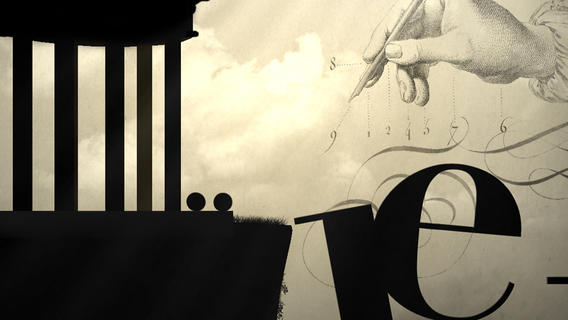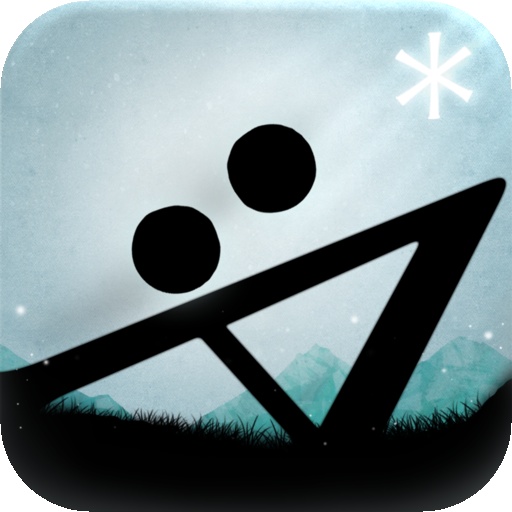
Pur essendo un gioco platform con elementi puzzle da risolvere Type:Rider di BulkyPix per iPhone e iPad brilla per la parte creativa e l’originalità del game design. Ogni elemento del gioco, i protagonisti e gli scenari sono infatti realizzati attingendo alla storia e agli elementi della tipografia: l’utente controlla due palline che devono rotolare e scalare percorsi costruiti con lettere e simboli grafici. I protagonisti, che sono la rappresentazione grafica dei due punti, iniziano il viaggio nel primo livello ispirato alle prime incisioni su pietra realizzate dall’uomo all’interno delle caverne, per proseguire lungo i 10 mondi in un affascinante viaggio che presenta gli uomini, le opere e soprattutto i font e gli stili grafici tipici di ogni epoca.
In puro stile platform dovremo così superare percorsi e baratri creati con lettere e caratteri proseguendo tra i geroglifici egiziani, la scrittura cinese, fino a epoche storiche più recenti come la frontiera americana dell’800 fino ad arrivare ai caratteri e alla grafica su computer. Nel corso del gioco l’utente dovrà raccogliere diverse lettere e potrà ammirare diverse tra le font più famose come Garamond, Helvetica, Times New Roman fino ad arrivare allo stile Pixel e Comimc Sans. In Type:Ryder tutti i caratteri e gli stili grafici prendono vita su schermo grazie a una grafica curata arricchita da un accompagnamento audio e musicale riuscito, in linea con l’epoca e lo stile rappresentati.
Nel corso dell’avventura dovremo gestire sia i movimenti delle due palline sia risolvere enigmi e puzzle lungo il percorso: raccogliendo degli speciali asterischi Type:Rider offre approfondimenti che permettono di scoprire la storia e gli uomini che hanno contribuito allo sviluppo della tipografia nel corso dei secoli.